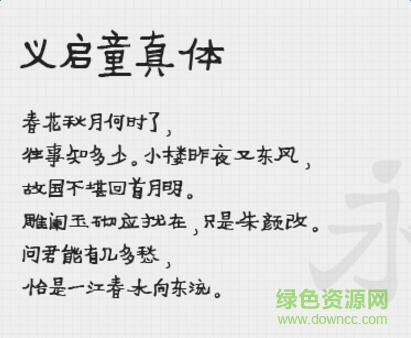
義啟童真體字體是一款義啟類(lèi)天真童趣風(fēng)格字體軟件,童真體盡顯兒時(shí)天真無(wú)邪,字體筆畫(huà)優(yōu)美,十分清新脫俗,整體效果非常可愛(ài),還有更多好看字體歡迎來(lái)綠色資源網(wǎng)下載體驗(yàn)!
義啟童真體字體是一款應(yīng)用于藝術(shù)設(shè)計(jì)方面的簡(jiǎn)體中文字體,該字體筆畫(huà)粗壯,尾部的甩尾有力且有豐富的筆觸細(xì)節(jié),大字效果突出且引人注目;并且最大程度還原作者書(shū)寫(xiě)字形,細(xì)節(jié)表現(xiàn)完整,且字庫(kù)完整,可以廣泛應(yīng)用于名片設(shè)計(jì)、新聞媒體、宣傳海報(bào)、ppt、影視制作以及內(nèi)容用字等領(lǐng)域。